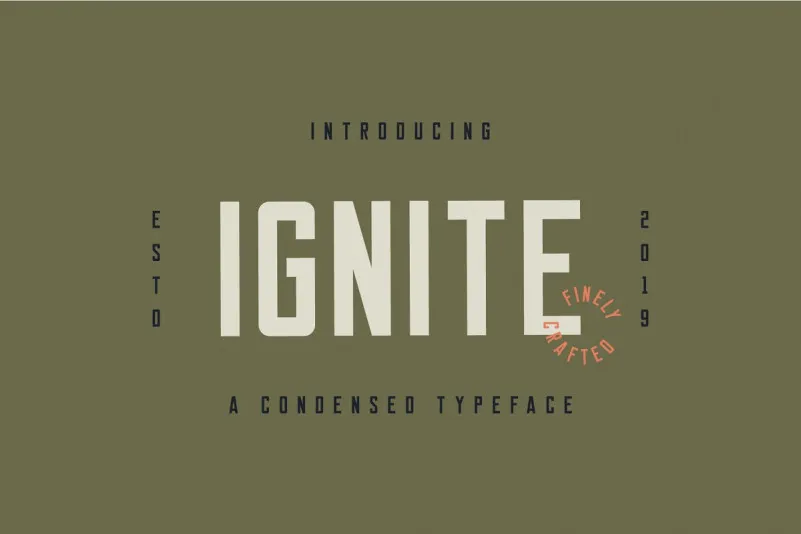
Ignite Sans Serif Font – Download Grátis
Olá amigo, apresentamos a você a fonte ‘Ignite Sans Serif’. Ignite é uma tipografia sans serif que se inspira em livros escolares antigos sobre escrita. É perfeitamente adequada para criar um estilo moderno e cuidadoso em seus projetos de design. Ignite combina perfeitamente com a identidade corporativa, logotipos, revistas, filmes, websites, cabeçalhos, subtítulos, jogos, aplicativos, cartazes e camisetas. Esta fonte oferece flexibilidade para uma variedade ampla de usos, tornando-a um excelente complemento em qualquer projeto visual. Se você está procurando por uma tipografia moderna que não se distingue pela curvatura dos caracteres, Ignite é sua fonte ideal.